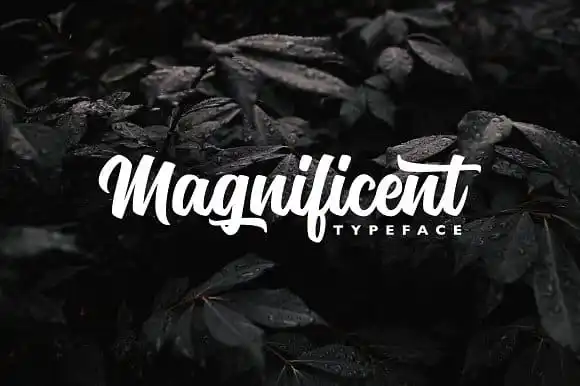
Magnificent Script Font – Download Grátis
Aqui está uma descrição para a página de download da fonte ‘Magnificent Script Font’, seguindo as instruções: Glad to introduce Magnificent Script Font! Este é um tipo de texto com personalidade, projetado pelo profissional Alex Couture, que lhe oferece a perfeita combinação entre formas elegantes e letras limpas. É uma fonte script ideal para aplicações visuais variadas. Construída em total harmonia com 254 caracteres, Magnificent Script Font é uma escolha perfeita para projetos gráficos que exigem expressividade e sofisticação. Seja um logo, um selo ou até mesmo um convite de casamento, este tipo de fonte garante visibilidade e design incrivelmente bonito. A Magnificent é perfeitamente adequada para aplicar em cartazes, camisetas, cartões de agradecimento ou até mesmo em materiais impressos como embalagens. Seja qual for seu projeto visual, você pode aproveitar as curvas sutis e fluidas desta fonte para criar mensagens atrativas e combinando alternativas de caracteres. A Magnificent Script Font é uma excelente escolha para designers que buscam adicionar um toque único a seus projetos visuais. Com sua beleza e facilidade na criação, ela se adequa perfeitamente tanto para propostas estilizadas quanto para aplicações mais diretas. Seja qual for o seu próximo projeto gráfico, Magnificent Script Font está aqui para ajudar você a destacar-se.